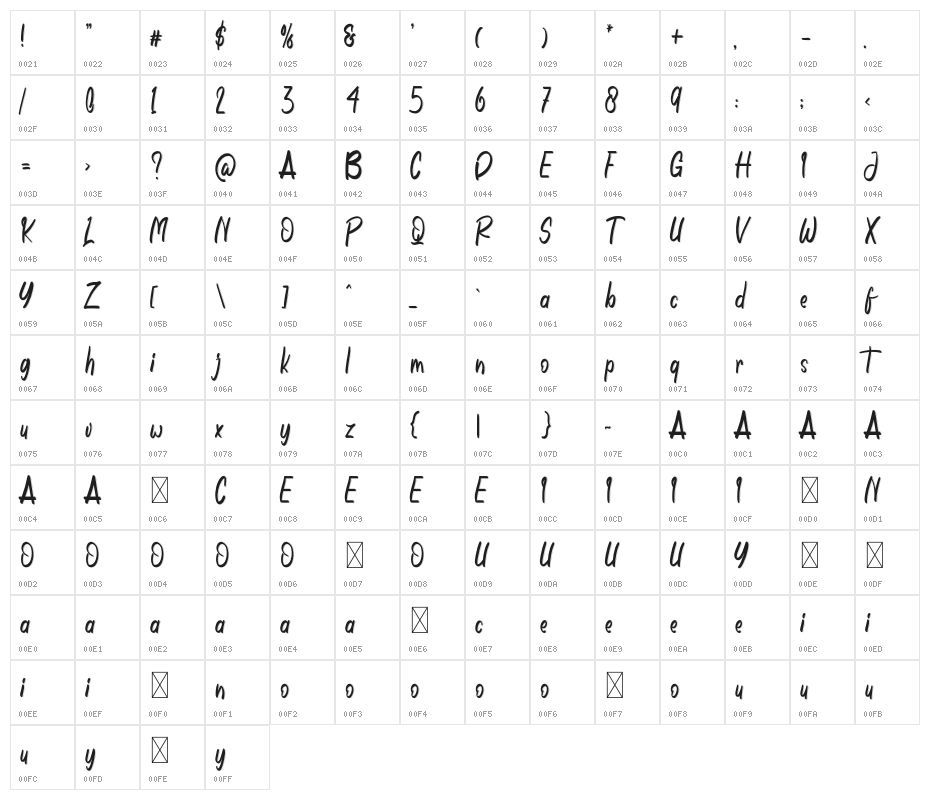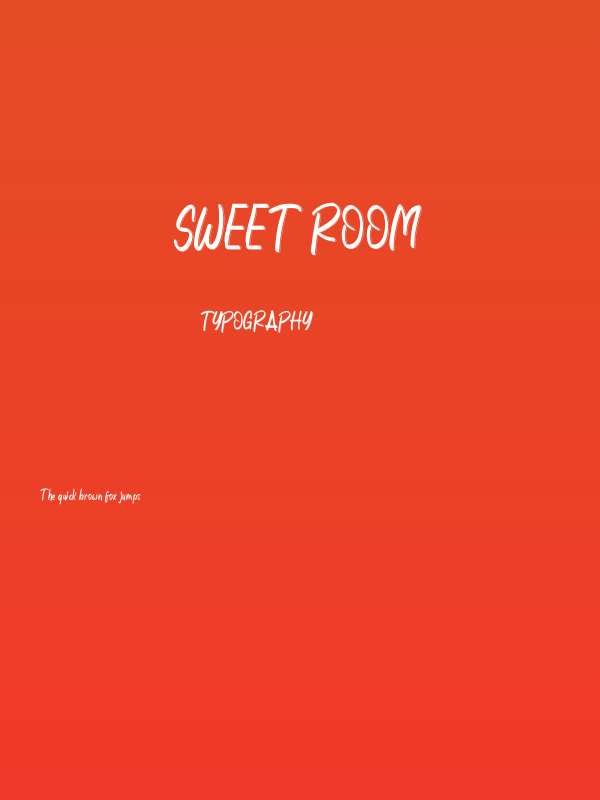
Sweet Room Font
✎ Comic
| Progetti proposti | Ideal for greeting cards, invitations, posters, and branding that require a personal and artistic touch. |